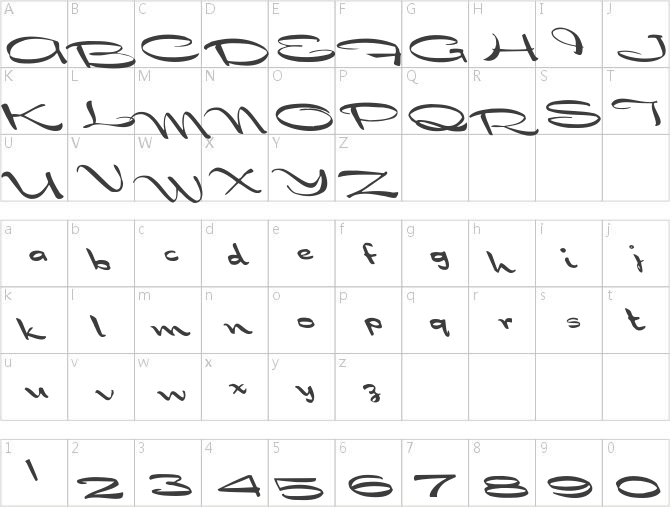
FZ JAZZY 31 LEFTY 詳情頁
字體名稱: FZ JAZZ
FZ JAZZY 31 LEFTY
FZ JAZZY 31 LEFTY字體字庫是一款讓人賞心悅目、百看不厭的英文字體,適合各類廣告和產品包裝設計應用,字體大小0.04MB,格式為ttf字體,上傳用戶是shiqiuping,作者/版權方為未知